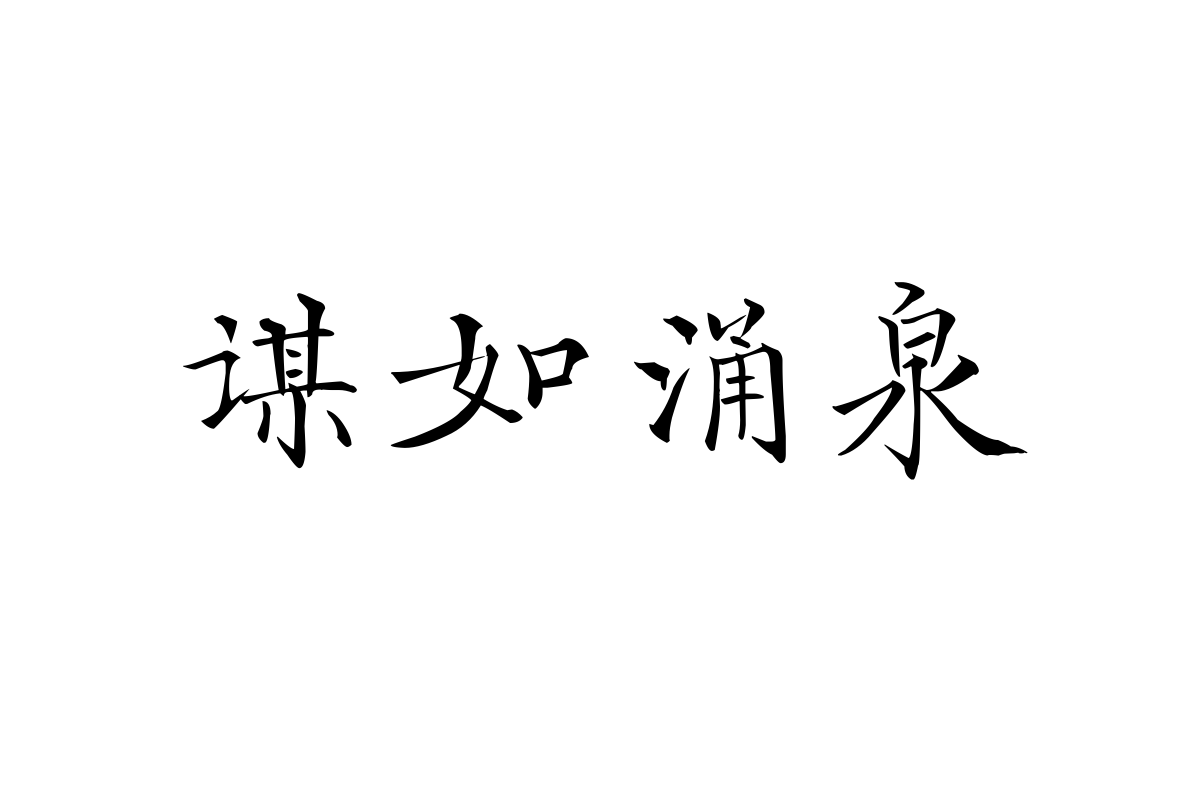
汉仪新蒂永乐大典是一款具有深厚文化底蕴的字体,其设计灵感来源于中国古代的永乐大典。这款字体采用了传统的书法风格,线条流畅、结构严谨,给人一种古朴典雅的感觉。同时,字体中的笔画粗细适中,既有力度感又不失柔美,使得整个字体既有古典韵味又不失现代感。
汉仪新蒂永乐大典适用于各种需要展示中国传统文化元素的场合,如书籍封面、海报、广告等。它不仅可以提升作品的艺术价值,还可以增强读者对中国传统文化的认知和理解。